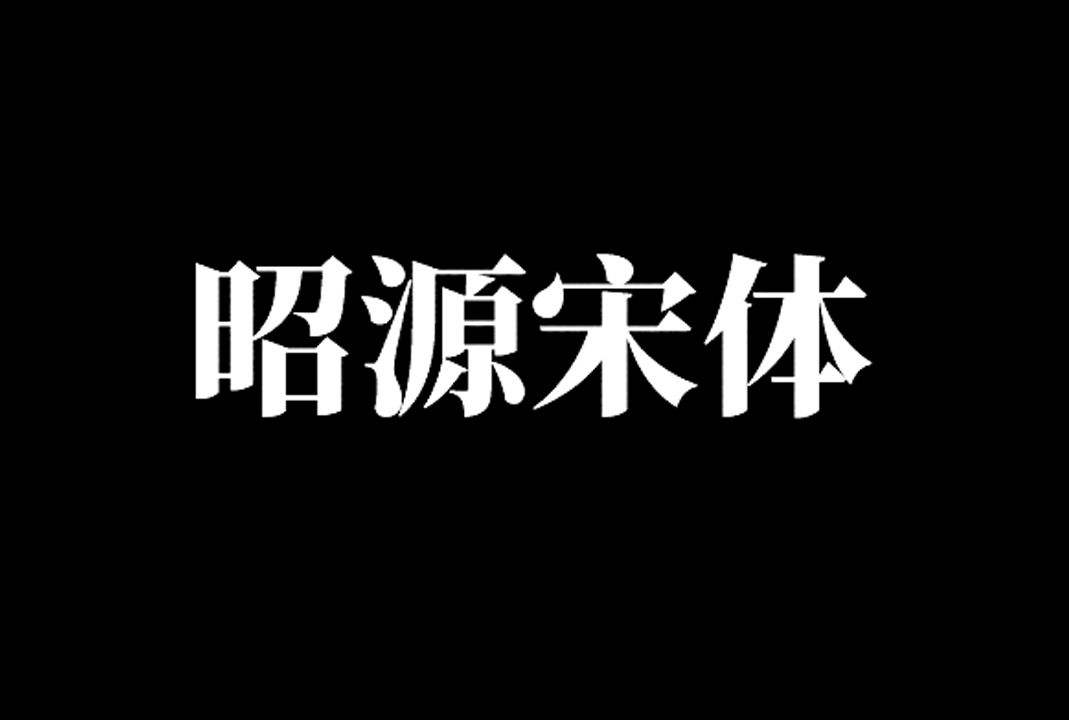
昭源宋体 (Chiron Sung HK) 是一款基于思源宋体香港版(Noto Sans CJK)改造的一款免费开源宋体字库,可配搭与之对应的昭源黑体/昭源黑体 Pro(昭源黑体为免费开源黑体) 使用。该字体收字量大、具现代感,屏幕显示、印刷皆宜。
昭源宋体提供和思源宋体相同的 7 款字重。除了个别中文字的字形经过修改,其他参数与思源宋体完全相同。
字重和字体名称:
Chiron Sung HK/HK TextChiron Sung HK VF字重值
ELExtraLight250
LLight300
NNormal350
RRegular400
MMedium500
SBSemiBold600
BBold700
HHeavy900